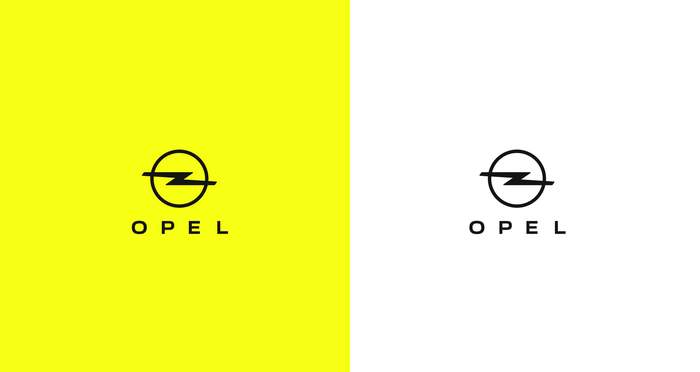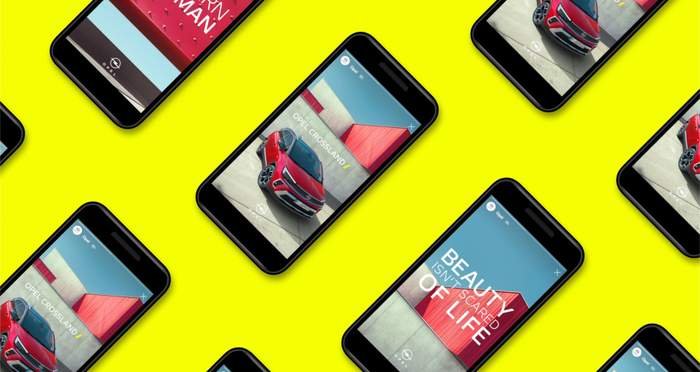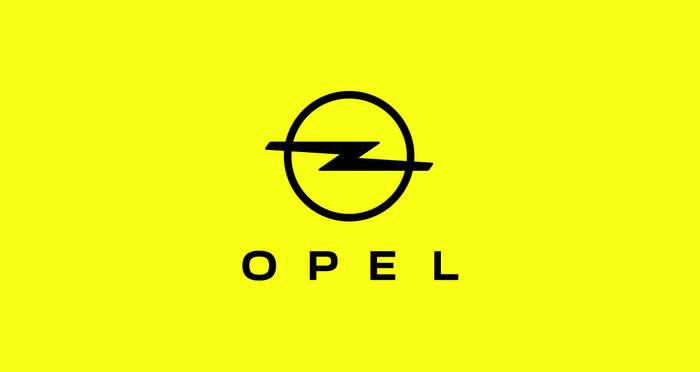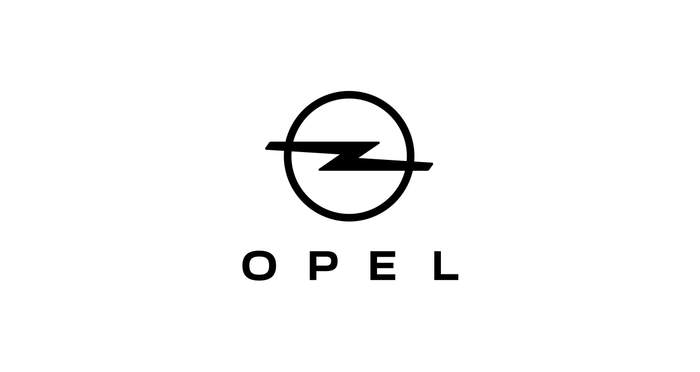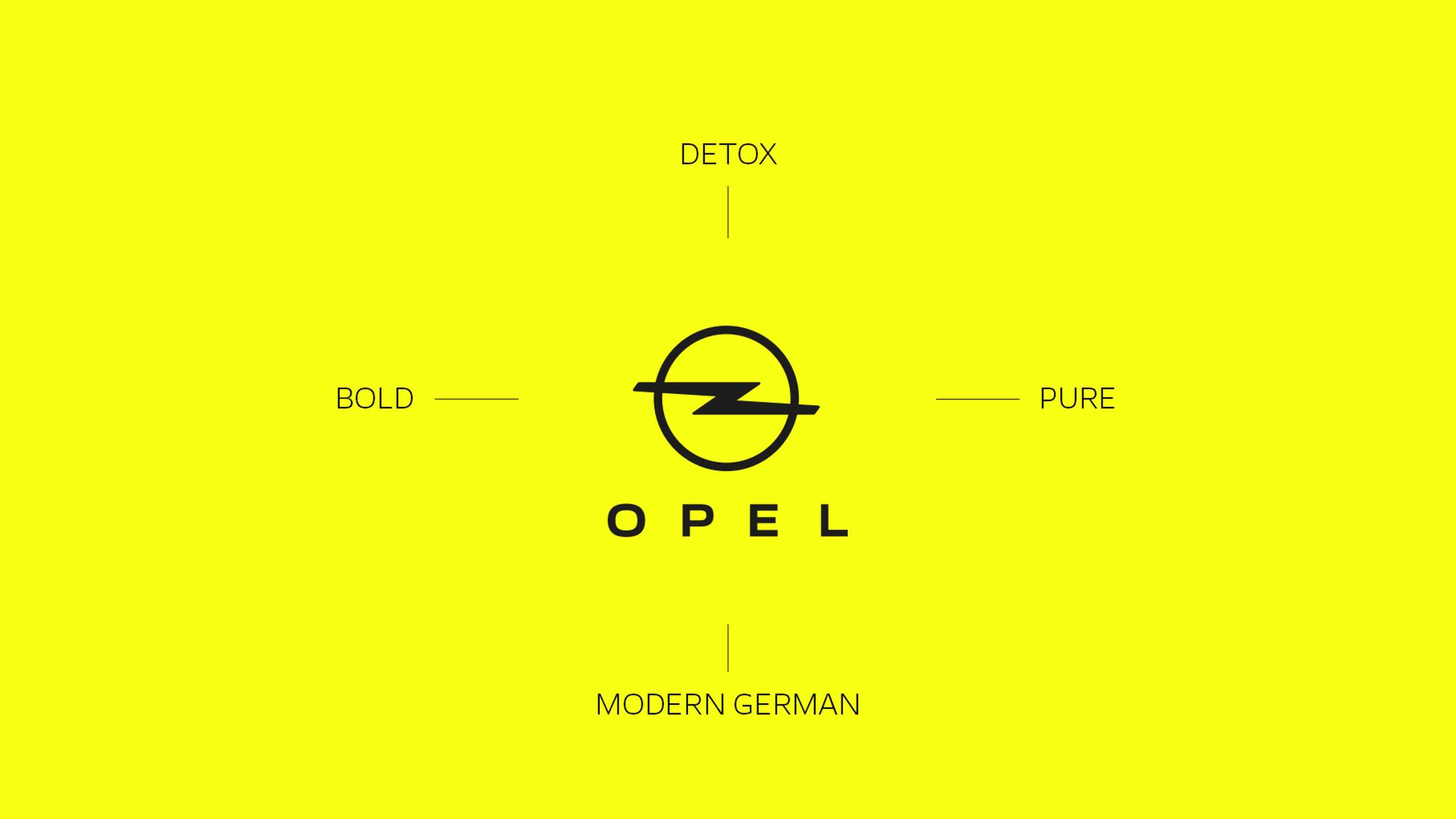
У Opel новый логотип, фирменный цвет и шрифт
Новая айдентика впервые появится на кроссовере Crossland.
У Opel новый логотип, фирменный цвет и шрифт
Компания Opel представила обновленный двухмерный логотип и фирменный желтый цвет. Также для бренда был создан собственный шрифт, получивший название Opel Next.
• "Новый Opel": современные элементы подчеркивают силу бренда к инновациям;
• Новый логотип: легендарный Opel Blitz в свежем дизайне;
• Новый шрифт: "Opel Next" – современный, выразительный и последовательный;
• Новый цвет: неоновый Opel – желтый выделяется и электрифицируют.
Opel отказался от трехмерной эмблемы, сведя графику к минимуму, чтобы подчеркнуть чистоту новой, цифровой эпохи. Акцент в новом логотипе сделан на изображении молнии, которая, благодаря тонкому ободу, стала более выразительной. Ранее по такой же схеме были обновлены фирменные знаки BMW, Volkswagen, Toyota и Nissan.
Новым фирменным оттенком компании стал ярко-желтый. Этот цвет является более выразительным и лучше запоминающимся. К тому же, его “неоновость” символизирует эпоху электрификации.
Все надписи – название марки, обозначение модели и т. д – теперь будут выполнены в легком и одновременно энергичному” фирменном шрифте, который получил название Opel Next.
Первым автомобилем с новым шильдиком станет кроссовер Crossland, построенный на платформе Peugeot 2008. Новинка появится в продаже в Европе в 2021 году.